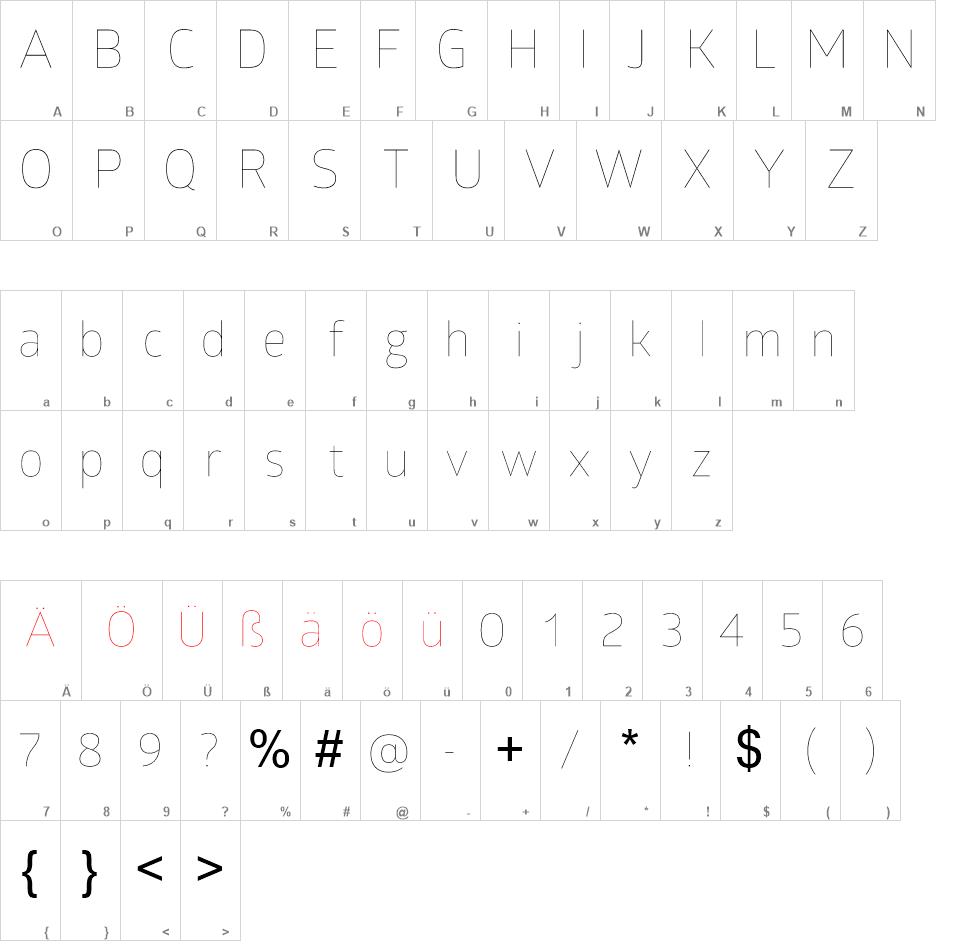
Glober
Glober font
Die Glober-Schriftfamilie enthält 18 Gewichte - neun kursiv neun vertikal. Sowohl der Web- als auch der Print-Design-Bereich zeichnen sich durch hervorragende Lesbarkeit in Bereichen wie gut vorbereitete geometrische Muster, optimiertes Kerning, hervorragende Webschriftarten und Lesbarkeit aus.
Inspiriert von der klassischen grotesken Schrift hat Glober seinen eigenen einzigartigen Stil in perfekt gemilderten geometrischen Formen.
Die Schriftfamilie eignet sich am besten für Titel mit beliebiger Größe sowie Blöcke mit maximalen und minimalen Abweichungen. Glober Schriftstile, Web, Print, Motion Graphics usw. Es gilt für alle Arten von Grafik-Design und ist perfekt für andere Gegenstände wie T-Shirts und Plakate, Logos.